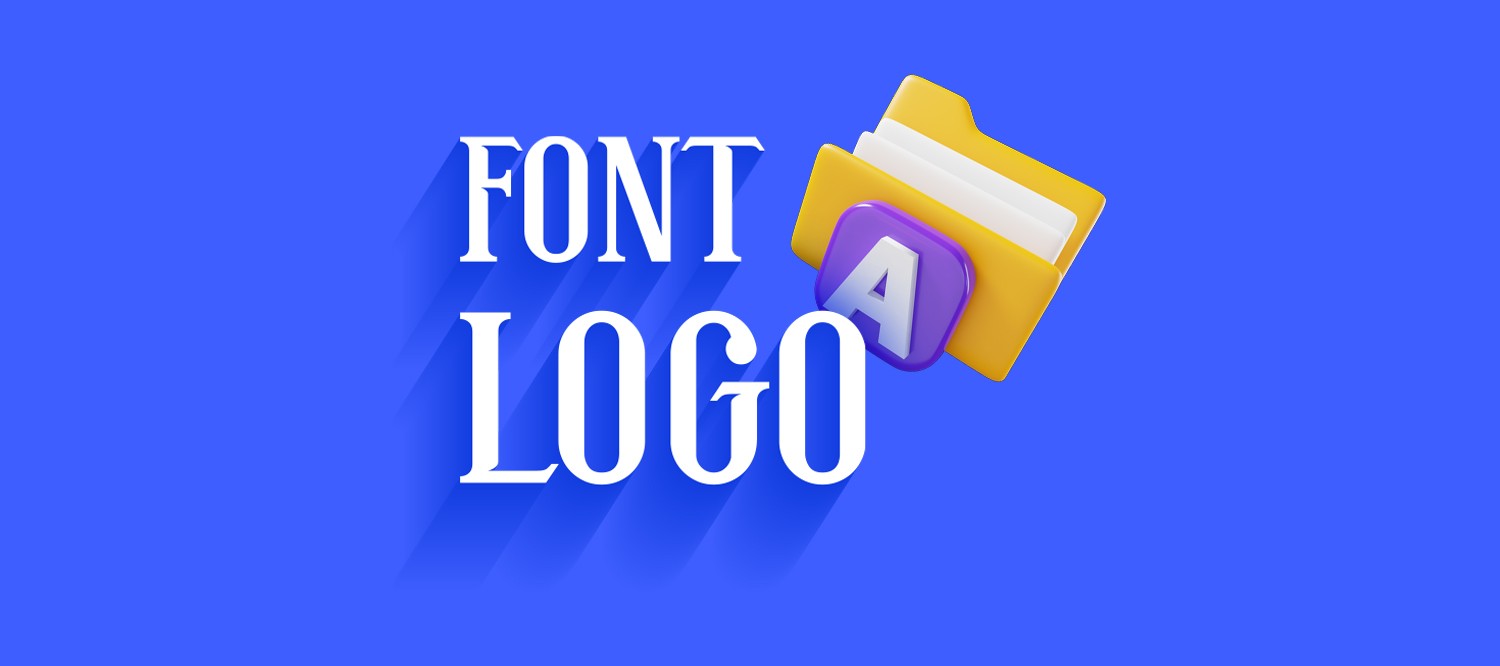
Khi thiết kế logo cho một thương hiệu, font chữ đóng vai trò quan trọng trong việc truyền tải thông điệp và phong cách của doanh nghiệp. Việc lựa chọn font chữ logo không chỉ đơn thuần là thẩm mỹ mà còn cần phải phù hợp với lĩnh vực hoạt động và giá trị cốt lõi của thương hiệu. Trong bài viết này, chúng ta sẽ khám phá cách lựa chọn font chữ logo chuyên nghiệp theo từng ngành nghề, đồng thời gợi ý những kiểu font phù hợp cho các lĩnh vực khác nhau.
Font chữ cứng cáp, bold thường có đường nét rõ ràng, dày dặn, mang lại cảm giác mạnh mẽ và vững chắc. Những font này thường được sử dụng để thể hiện sự uy tín, đáng tin cậy, phù hợp với các ngành nghề yêu cầu sự mạnh mẽ và tính ổn định cao.
Ứng dụng vào lĩnh vực:
Xây dựng: Ngành xây dựng đòi hỏi logo thể hiện sự bền vững, kiên cố. Các font chữ bold và chắc chắn rất thích hợp để truyền tải thông điệp về sức mạnh và độ tin cậy.
Kỹ thuật: Tương tự như xây dựng, các ngành kỹ thuật cần những font chữ thể hiện sự chính xác và chắc chắn.
Thể thao: Font chữ cho ngành thể thao thường mang phong cách mạnh mẽ, góc cạnh và đầy năng lượng để thể hiện tính chất vận động, sức mạnh và sự quyết tâm. Các font chữ này có thể là những font sans-serif đậm hoặc các kiểu chữ cách điệu để nhấn mạnh sự chuyển động và tốc độ.
Font chữ mảnh mai, mềm mại thường mang lại cảm giác thanh lịch, tinh tế và sang trọng. Những font này có độ mảnh vừa phải, giúp logo của bạn trông nhẹ nhàng mà không quá phô trương.
Ứng dụng vào lĩnh vực
Spa & Làm đẹp: Các doanh nghiệp trong lĩnh vực này thường muốn tạo ra cảm giác thư giãn, yên bình. Font chữ nét mảnh mang lại sự thanh thoát và sang trọng cho logo thương hiệu, đồng thời thể hiện sự chuyên nghiệp và tinh tế.
Thời trang cao cấp: Các thương hiệu thời trang đẳng cấp cũng cần những font chữ thanh thoát để thể hiện sự tinh tế và độc đáo. Font chữ serif lựa chọn tuyệt vời để nhấn mạnh sự sang trọng và phong cách.
Những font chữ cute, thân thiện thường có các đường nét mềm mại, dễ thương và tạo cảm giác gần gũi. Đối với ngành thực phẩm, đặc biệt là các cửa hàng ăn uống hay thương hiệu thực phẩm dành cho trẻ em, font chữ thân thiện giúp thương hiệu trông hấp dẫn và dễ tiếp cận hơn.
Ứng dụng vào lĩnh vực:
Cửa hàng bánh ngọt, quán cà phê: Các cửa hàng bánh hoặc quán cà phê thường sử dụng những font chữ vui tươi để tạo sự gần gũi với khách hàng, mang đến cảm giác thoải mái và vui vẻ.
Thực phẩm cho trẻ em: Trong lĩnh vực này, các font chữ tròn trịa và dễ thương là lựa chọn tuyệt vời để tạo nên sự gần gũi và thân thiện cho các thương hiệu đồ ăn trẻ em.
Font chữ hoạt hình TH Lusiana Việt Hóa | Link tải
Font chữ hoạt hình, cute béo tròn SVN-Ziclets Việt hóa | Link tải
Những font chữ logo mang phong cách vintage thường mang lại cảm giác hoài cổ, truyền thống nhưng vẫn rất độc đáo và cuốn hút. Loại font này thích hợp với những thương hiệu muốn tạo nên sự khác biệt bằng cách khai thác yếu tố lịch sử hoặc hoài niệm.
Ứng dụng vào lĩnh vực
Ngành du lịch: Đối với các thương hiệu du lịch, đặc biệt là những doanh nghiệp tập trung vào các tour du lịch khám phá hay trải nghiệm văn hóa, việc sử dụng các font chữ vintage có thể giúp mang lại cảm giác mới mẻ nhưng vẫn gắn kết với yếu tố truyền thống và hoài niệm.
Ngành giải trí: Các sự kiện hoặc dịch vụ giải trí cổ điển cũng thường sử dụng font chữ vintage để tạo sự khác biệt và nổi bật, mang lại cảm giác gần gũi nhưng cũng đầy tính sáng tạo.
Gợi ý font chữ tại S99.vn để bạn tham khảo:
7 font chữ phong cách hoài cổ xưa cũ DT Phudu | Link tải
Font chữ TH Juzho Kaizen phong cách Nhật Bản Việt hóa | Link tải
Font chứ cố điển Việt hóa TH Hustle Culture | Link tải
Font chữ cổ trang Việt hóa NVN Morning Calm | Link tải
Lựa chọn font chữ logo là một bước quan trọng trong quá trình xây dựng thương hiệu, ảnh hưởng lớn đến cách mà khách hàng nhận diện và cảm nhận doanh nghiệp. Mỗi ngành nghề đều có những yêu cầu riêng về font chữ, từ những font cứng cáp mạnh mẽ cho ngành xây dựng đến những font mềm mại, sang trọng cho ngành làm đẹp.
Việc hiểu rõ đặc điểm và ứng dụng của từng loại font sẽ giúp bạn tạo ra một logo ấn tượng và chuyên nghiệp, phù hợp với lĩnh vực hoạt động của thương hiệu. Hãy nhớ rằng, một font chữ logo tốt không chỉ đẹp mắt mà còn phải truyền tải đúng thông điệp và giá trị của doanh nghiệp.